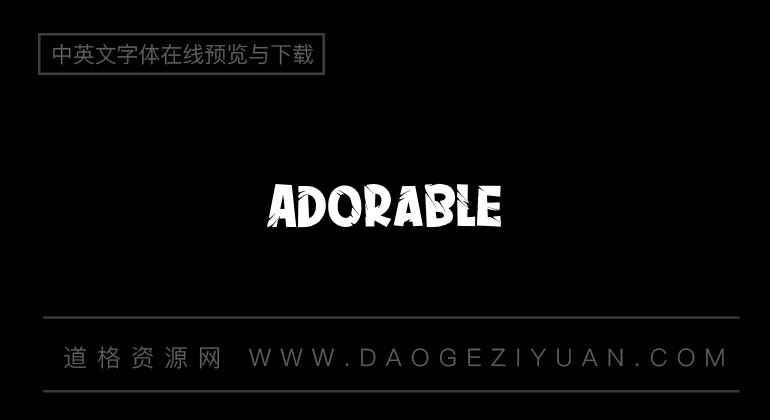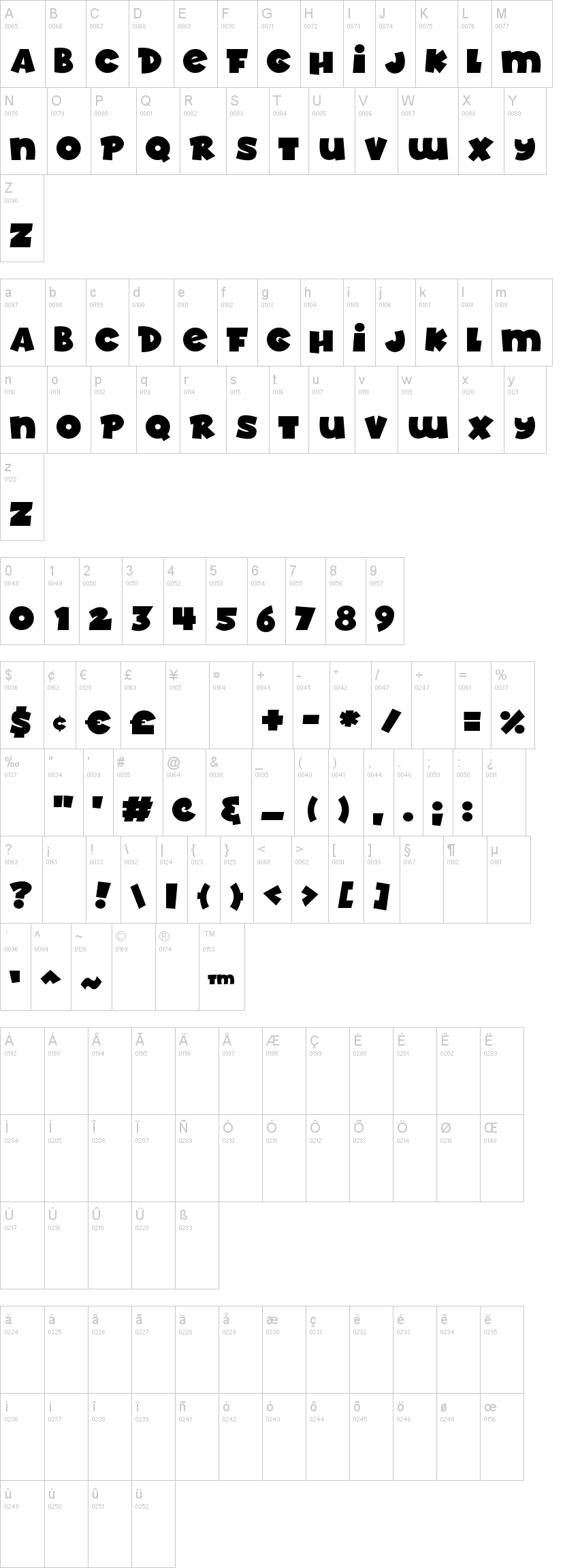
Adorable是一款非常可爱的字体,它采用了圆润的设计,给人一种温暖、友好的感觉。这款字体的特点是字母之间的间距比较小,字母形状较为简洁,整体视觉效果非常舒适。 Adorable字体适用于各种场合,比如儿童书籍、卡通动画、广告宣传等。它的可爱风格很容易吸引人们的注意力,是一种非常受欢迎的设计风格。 此外,Adorable字体还有一些变体,比如Adorable Bold、Adorable Italic等。不同的变体可以满足不同的设计需求,让设计师更加灵活地运用这种字体。内容介绍
Adorable是一款非常不错的手写艺术字体,具有很好的视觉感,适合于文化类的宣传设计、商业类品牌的广告和产品包装设计以及个性化文字排版等较多场景。